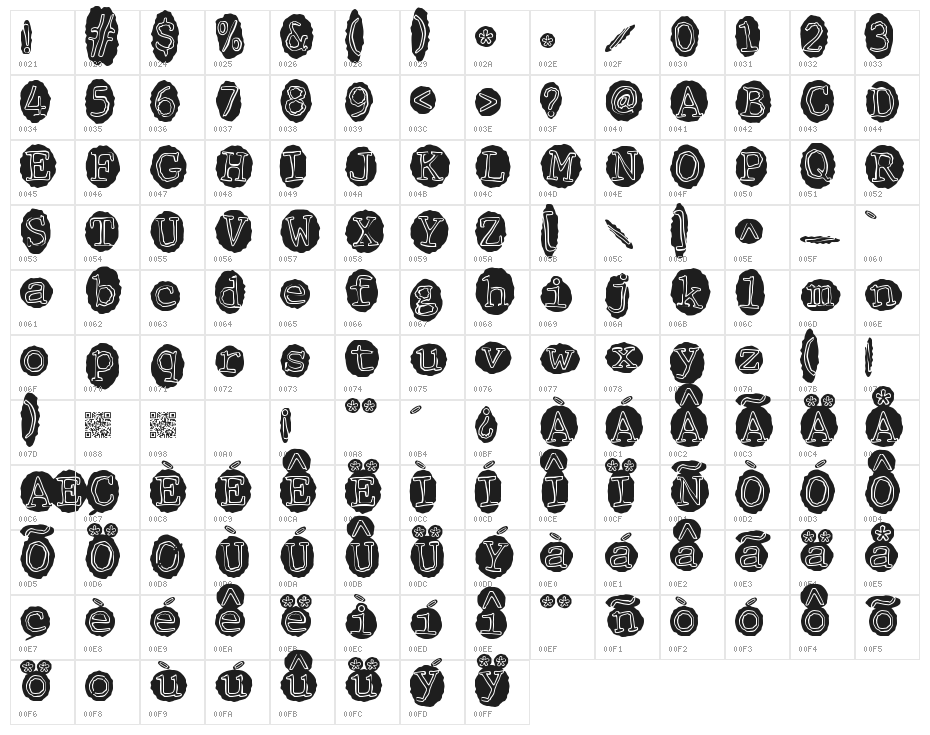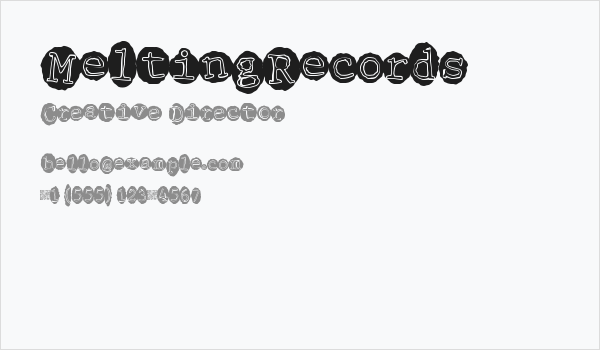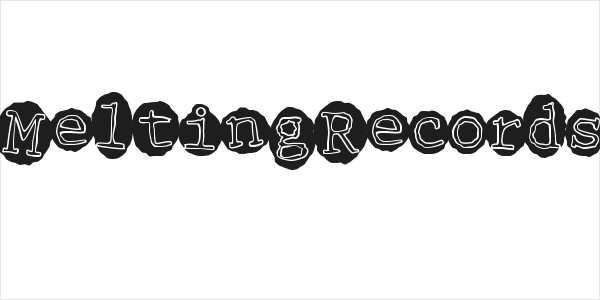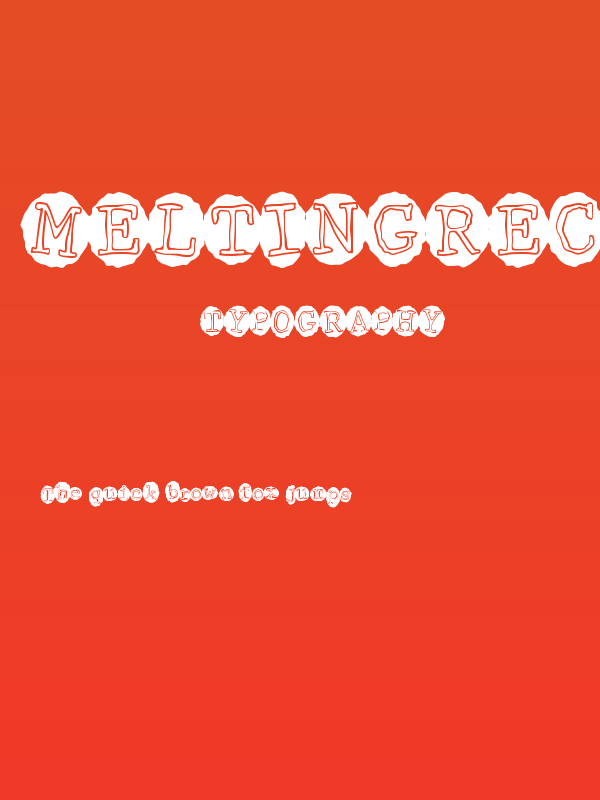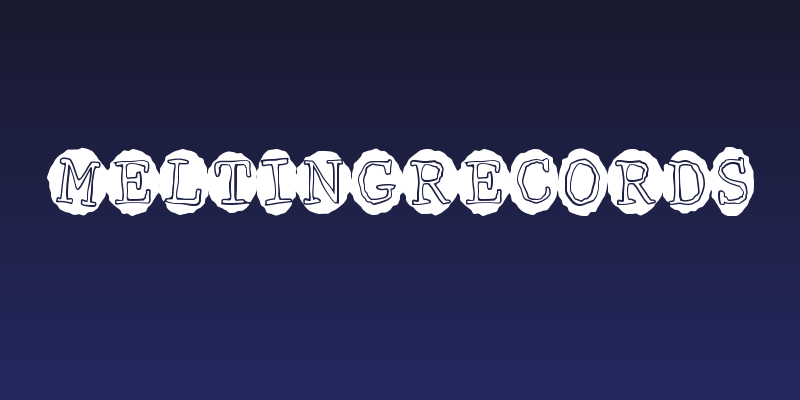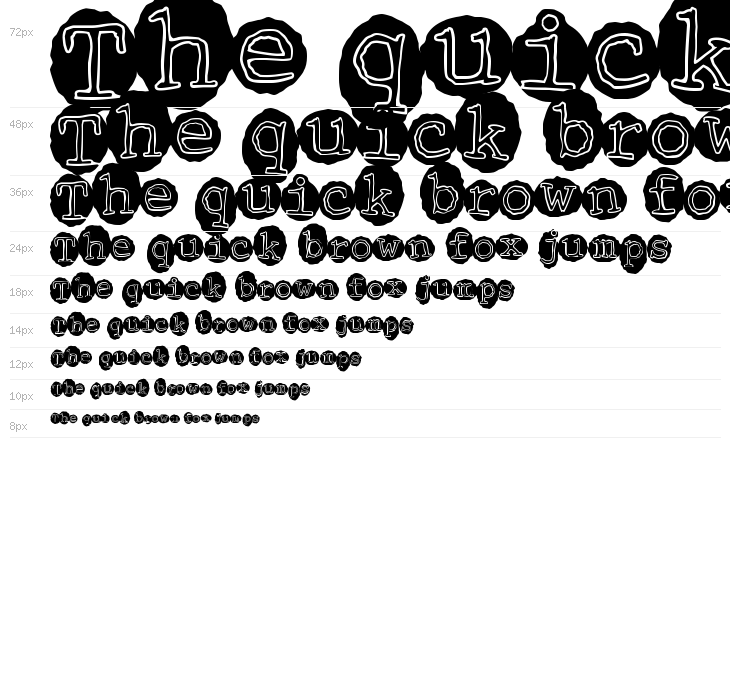
MeltingRecords Font
| Vorgeschlagene Projekte | Perfect for album covers, posters, event flyers, and any creative project needing a bold, artistic touch. |